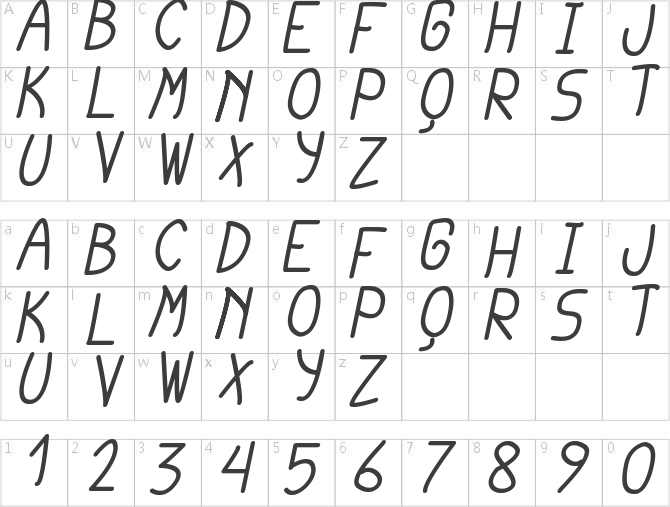
cursi extra tfb bold cursive 詳情頁(yè)
cursi extra tfb bold cursive字體字庫(kù)是一款讓人賞心悅目、百看不厭的英文字體,適合各類廣告和產(chǎn)品包裝設(shè)計(jì)應(yīng)用,字體大小0.01MB,格式為ttf字體,上傳用戶是惠祥博達(dá),作者/版權(quán)方為未知